卡通风格的 LOGO ,通常会给人以乐趣、快乐、愉悦这样的情绪。那些竭尽全力想要被接纳的品牌,通常会尽力去使用专业的设计,来赢得用户的青睐。在即将到来的 2020 年,卡通风格的 LOGO 会更加受欢迎,同时,这些 LOGO 的设计可能还是动画化的。动态的卡通 LOGO 会看起来更加具有趣味性,更容易打破用户和品牌之间的隔阂——因为这样看起来更加友好、有趣。
1.1 描边卡通样式
带有粗描边的卡通样式 LOGO 是大热的设计样式,它也是 2020 年最主要的趋势之一。这些LOGO 插画看起来有趣无比,无论大小尺寸看起来都很不错。
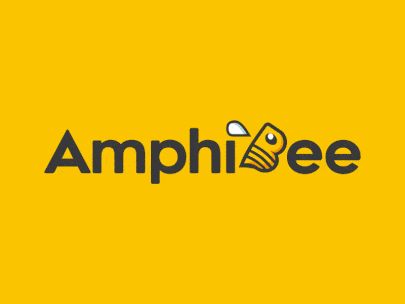
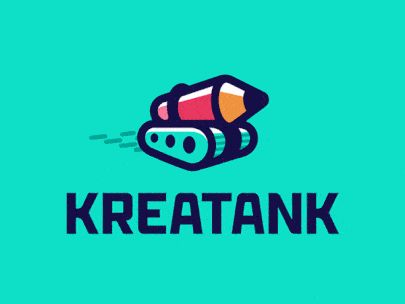
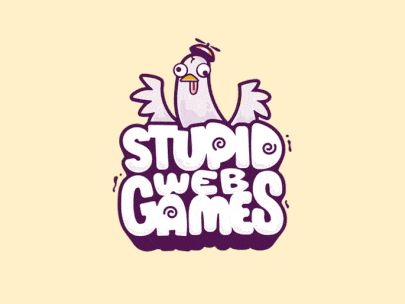
1.2 扁平卡通样式
相对而言,设计师会更加青睐简约的样式,这也是扁平化的卡通 LOGO 样式会这么流行的原因之一。就像下面的案例,这些 LOGO 通常就保留一些相对简化的轮廓,适当加入一些有趣的动画,让它们变得足够生动。
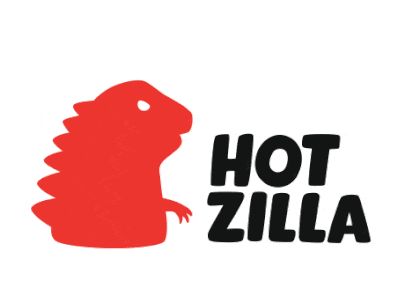
1.3 涂鸦卡通风格
卡通涂鸦风格也是一个稳健扎实的趋势。类似记号笔和铅笔的涂鸦让 LOGO 更加具有质感。这样的 LOGO 设计更好地保留了手作感。
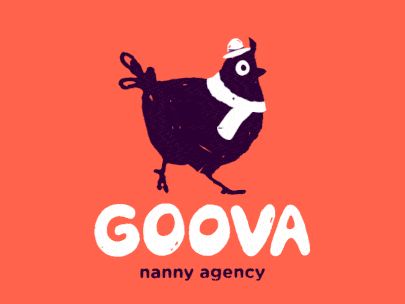
黑白 LOGO 永远不会过时。它们优雅,简约,不会分散用户注意力,并且适配几乎所有的设计。在绝大多数的情况下,设计师通常会创建彩色和单独的黑白版本,但是有的时候,黑白版本的设计足够优秀,甚至都不用设计彩色的版本。下面是一些令人印象深刻的黑白 LOGO 设计。
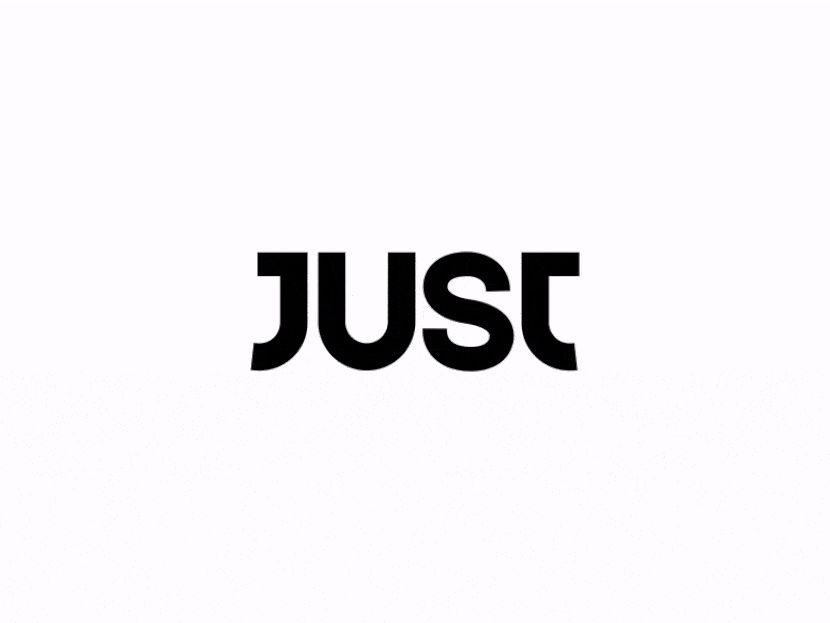
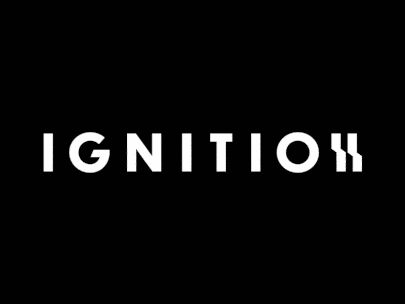
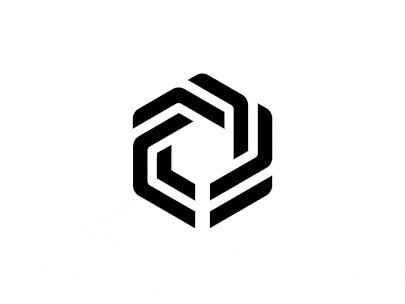
LOGO 通常在设计时会带有隐喻,当然,最重要的还是要体现品牌本身的特色和气质,所以设计师需要借助不同的技术和丰富的设计手法来替品牌发声,还要保持简约。所以很多设计师会巧妙地使用负空间来进行绘制。
高度抽象的几何图形能够让 LOGO 的视觉更容易脱颖而出。简约的 LOGO 设计如今也是整个 LOGO 设计行业中的首选风格之一。能够简单轻松地被人了解和识别也是 LOGO 设计的目标,因此很多品牌也更加青睐这样的设计。这样的 LOGO 会更加令人难忘,设计师通常会使用独特配色的版本,并且保留一个黑白单色的版本。
方形是稳定和平衡的象征,因此品牌设计通常会希望借助方形来表达这样的气场或感觉。在接下来的 2020 年,方形可能会是更加受欢迎的选择,而负空间的运用也将更多地与之结合到一起。
基于线条的 LOGO 设计也是流行的选择之一。它们经常被用来构建一些基本的图形或者视觉元素,你会发现线条在 LOGO 设计当中会显得更加自由、简约和开放。我们可能会注意到更多运用线条来构建的图标设计。
另一方面,曲线元素的运用也是一大亮点趋势。曲线常常会蕴含有「动力」和「创造」这样的概念,而设计师几乎可以拿曲线画出任何东西。我们接下来可能会看到各式各样的曲线,嵌入到 LOGO 的各种地方。
圆形和环形的 LOGO 也是一个大热的设计趋势,对于这一点我们从来都不会感到惊讶。作为最基本的几何元素之一,圆形具有非常强烈的隐喻——完美,无限等等。在 LOGO 方面,LOGO 设计师常常会将粗细不一的字体结合到一起,让 LOGO 的感觉更加鲜明。
另外,值得一提的是,无限符号(∞) 也是一个非常高频次出现的 LOGO 设计元素。设计师通常会将它融入到图形或者文字当中,这种带有「永无止境」概念的符号非常受青睐。
一种颜色不够用的时候,渐变就发挥作用了。渐变色的 LOGO 设计是这两年才开始大规模流行的一种设计,这种用色技巧能够将 LOGO 视觉变得层次更加丰富,色彩的微妙变化让 LOGO 更加富于动感,更加迷人。
5.1、多色渐变
LOGO 中最流行的渐变用法之一是多色渐变。明亮生动的色彩构建成为漂亮的配色方案,如果想让配色方案更加自然,可以采用自然界当中存在的色彩渐变,比如日落的天空。也可以使用更加独创、创新的梦幻配色。
5.2、近似色渐变
当然,也有设计师会青睐于相对更加克制的配色方案,甚至仅在一个色相内取色,让 LOGO 的视觉更加集中、更加遵循品牌对于颜色的要求。这并不意味着这样的 LOGO 配色设计不够动感,实际上这样的设计会显得更加微妙有趣,更有品牌凝聚力。
总的来说,复古是2020年平面视觉设计的重要趋势之一,LOGO 的复古风可以说是它的延续。做旧的纸张效果,故障风格,复古的图案,充满时代感的配色方案,我们可以在太多的地方看到这样的复古 LOGO 设计。复古风 LOGO 卷土重来,这是大趋势。
在 LOGO 当中使用金属元素(比如金色和银色),一直是创造高级感的实用方法。除了为数字版的 LOGO 制作金属质感之外,在印刷品上为 LOGO 附上特殊质感也相当出效果,无论是印刷在名片还是宣传单,还是其他物料上,都会相当引人瞩目。如果将这种金属材质和镂空效果结合起来,能制作出更加独特的定制感和裁剪感。
越来越多的 LOGO 当中都不再使用复杂的图形元素,使用高度定制化的文本字体 LOGO 已经是设计师和企业的首选了。在最新的 LOGO 设计中,我们注意到,有的LOGO字体会选择直白的表达,有的设计选择了巧妙的双关或者隐藏式的表达。
等轴测的 LOGO 设计和 3D 化的 LOGO 比起以往多了不少,可以说是最为醒目的设计趋势之一。在 2D 的平面上描绘 3D 的对象,它们比起常规的平面设计更具纵深,如果再搭配上时尚的外观,比如渐变色和光影,LOGO 无疑更加具有张力。
半透明的设计无疑显得更加现代。在我们看来,这种趋势在 2020 年会更多,半透明的设计不仅更加炫酷,而且具有更重要的意义:它能传达出品牌本身的通透,更容易建立信任感。
虽然我们说 LOGO 设计趋势的变化相对缓慢,但是我们依然看到了这一领域的变化。相比于前几年对于简约的疯狂迷恋,在 2019 年和即将到来的 2020 年,我们将会迎来更多丰富多彩的设计,卡通风格,巧妙的视觉构建,渐变和纯色的交汇,更为现代的半透明的设计穿插在黑白经典的 LOGO 当中,令人期待。